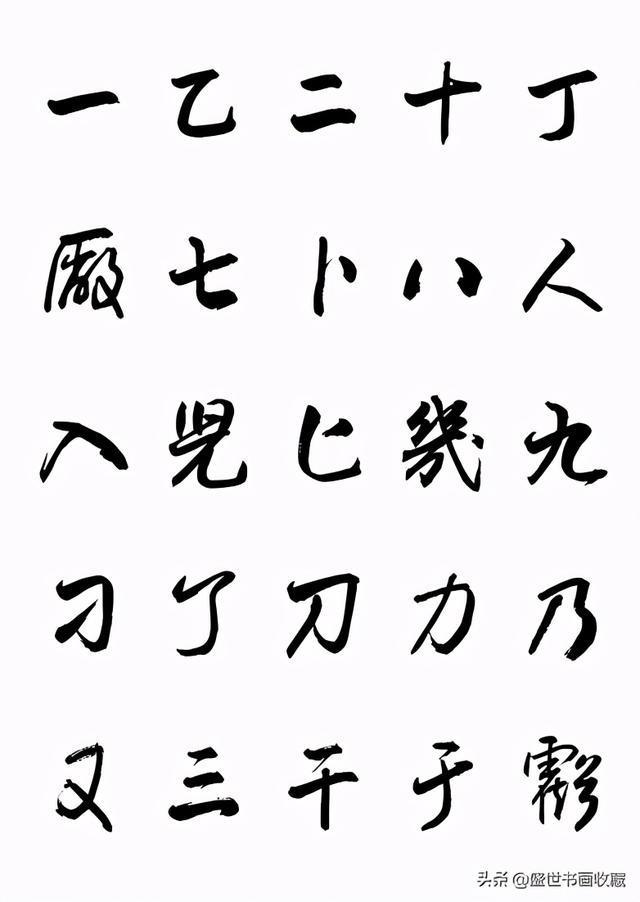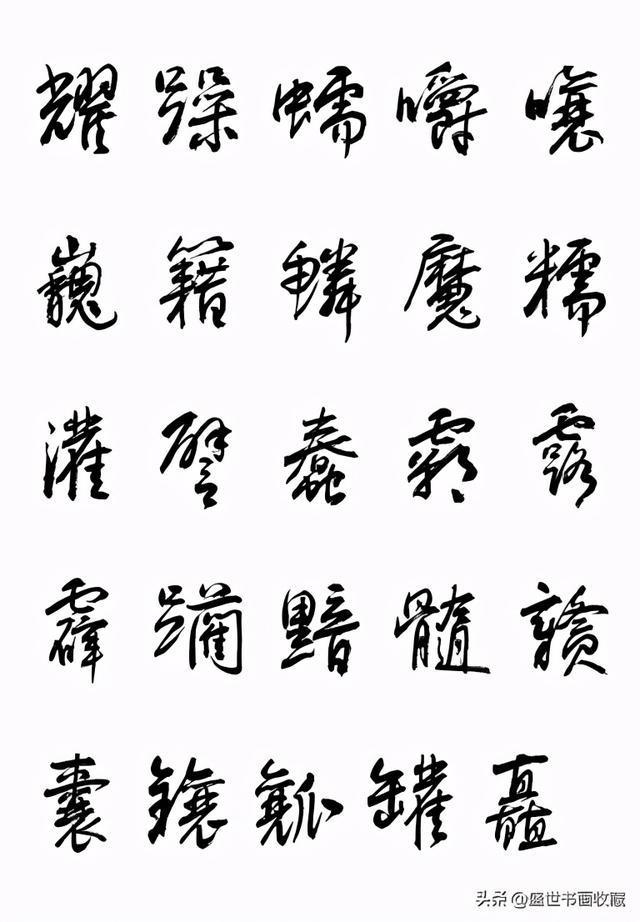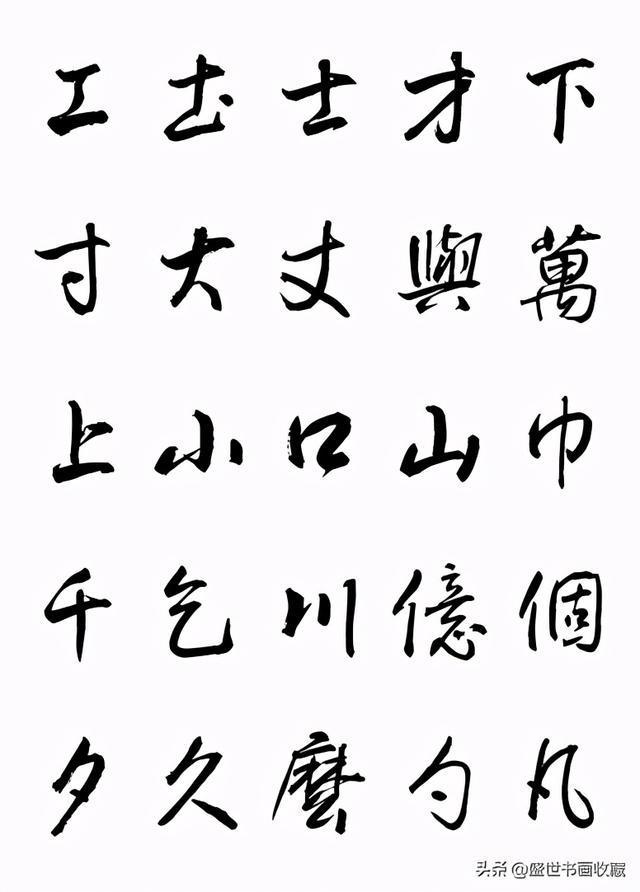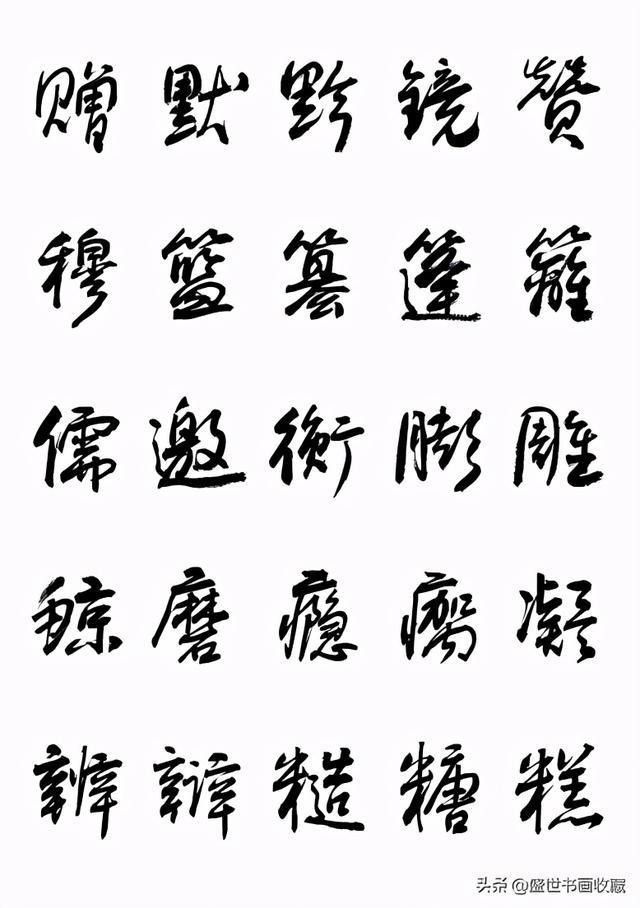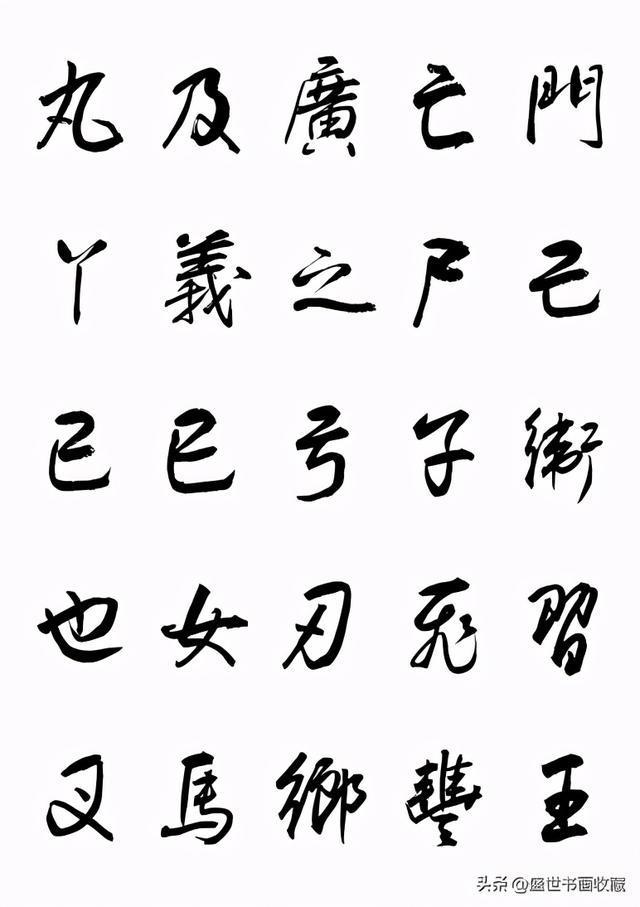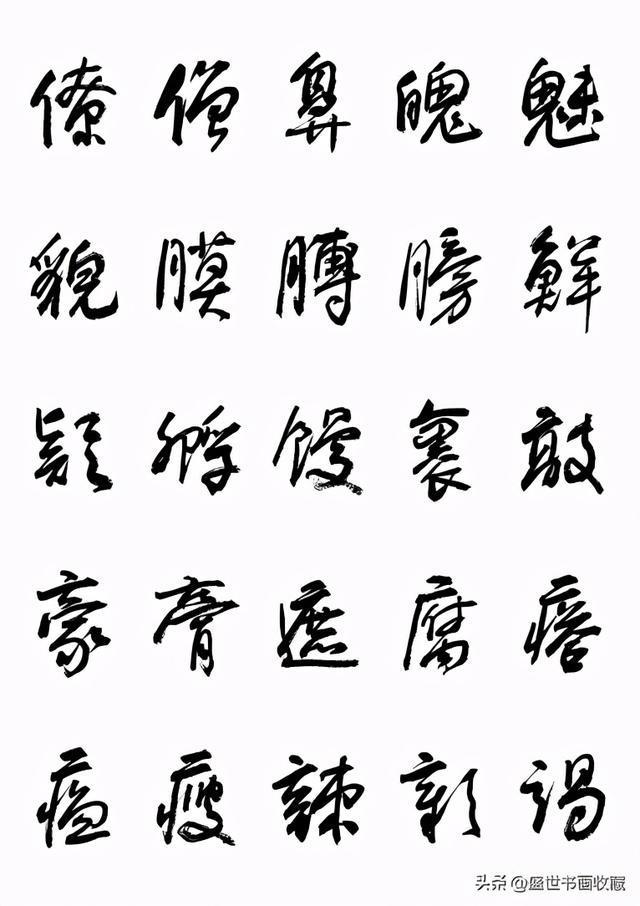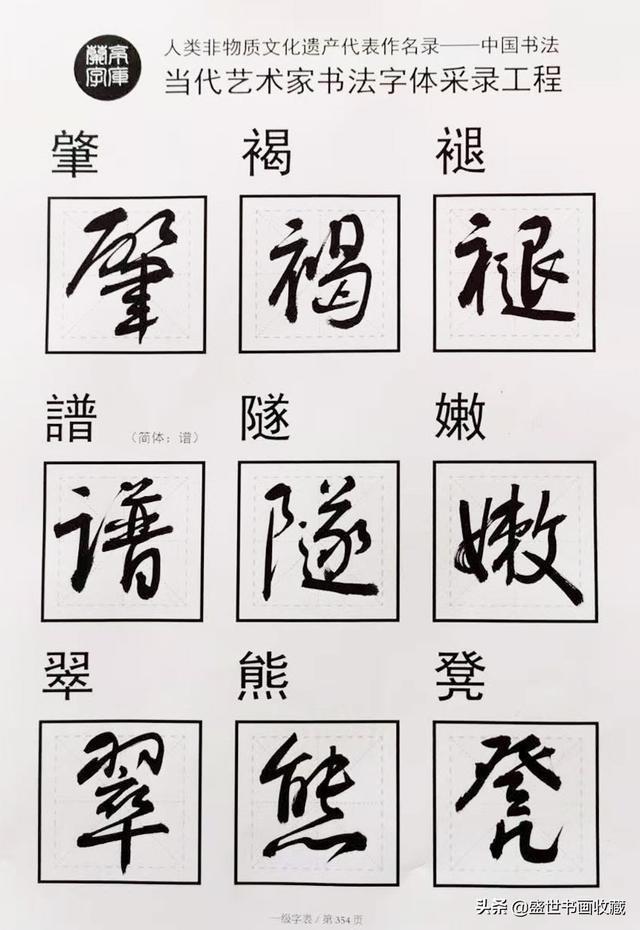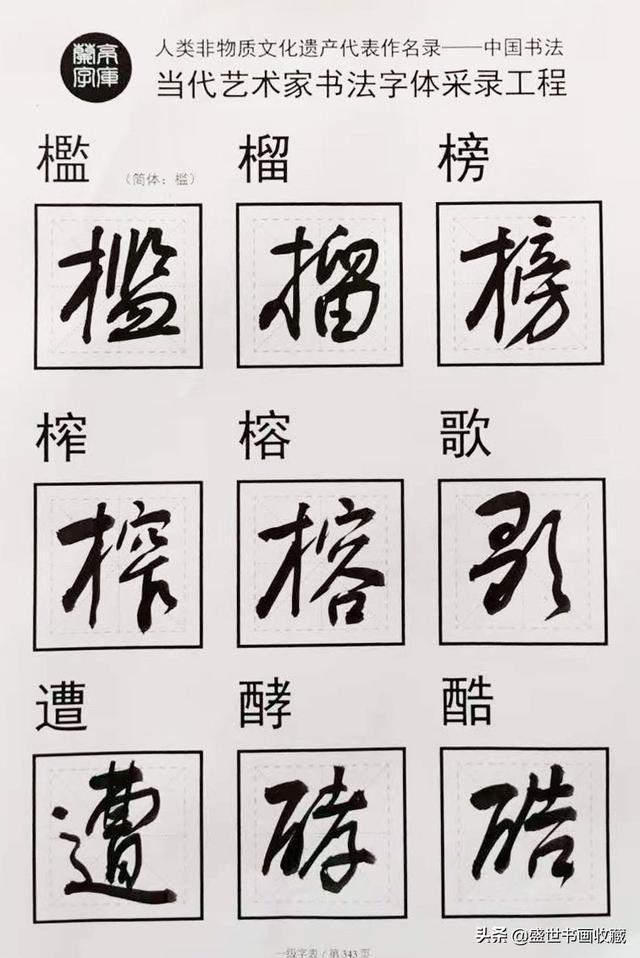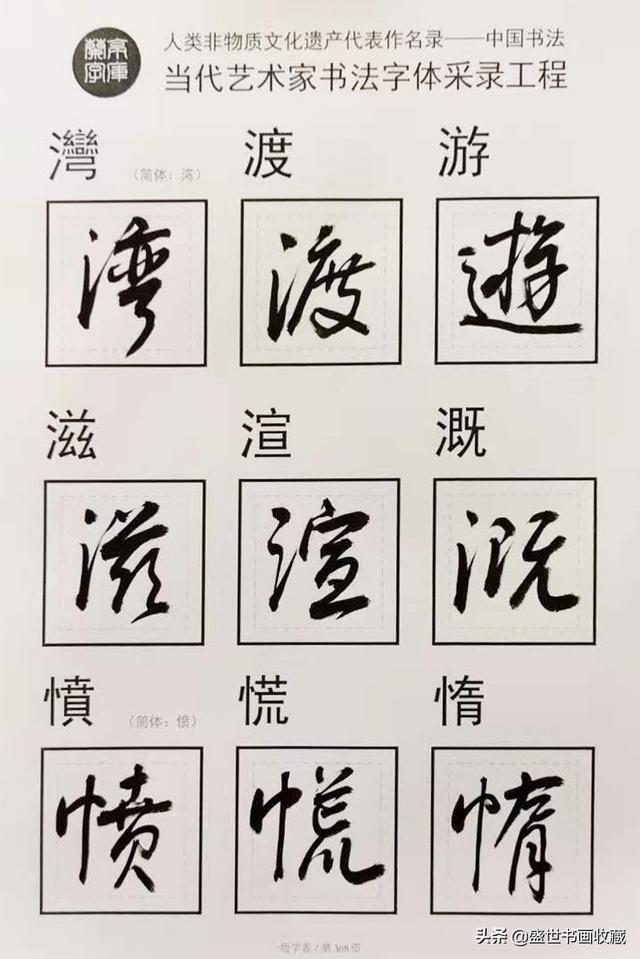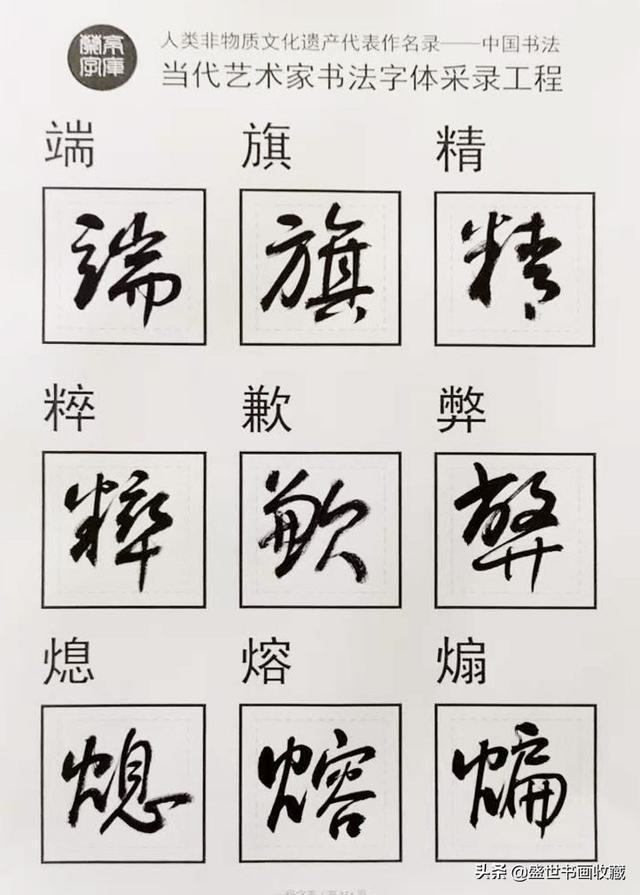
有着六十余年学书经历的黄彬老师,最近完成了一件工程:为兰亭字库书写了一套书法字,约5000字,制作方命名为“黄彬体”。在百度网上发布后,获得好评。黄彬老师根据制作方提出的”实用,便于传播、推广"的要求,在保留个人书法风貌基础上,采取“行草结合,繁简结合,艺术适用结合,可识,好用”,历时半年写完了这套字。也是其对书法如何面向社会作了新尝试。
黄彬老师表示,由于受提供的用纸及固定格式限制,字写得比较拘谨,缺少变化。以下是黄彬老师新近创作的作品。与“字库字"相比,多了几份舒展、典雅、灵动,体现他的独特風格。
黄彬,湖南岳阳平江人,中国书法家协会会员、中央国家机关书法家协会副主席、湖南省书法家协会顾问。学书幼承私塾启蒙,临帖自修,染翰60余載。曾就读首都师范大学书法硕士课程班(两年),师从欧阳中石,得叶培贵、甘中流、解小青、云志功、张同印等名师指导。书崇“二王”,主攻行草。书风格调高雅、自然流畅。2014年起,在北京、长沙、广州、梅县、重庆等地举办个人巡展。作品曾在纽约时代广场大屏幕展播。多幅作品在保利公司拍卖成交。热心公益,弘扬传统。实力派书法家。中央电视台等有专题报道。军队职务:国防大学原教研室主任、教授、博导、少将。享受特殊津贴。